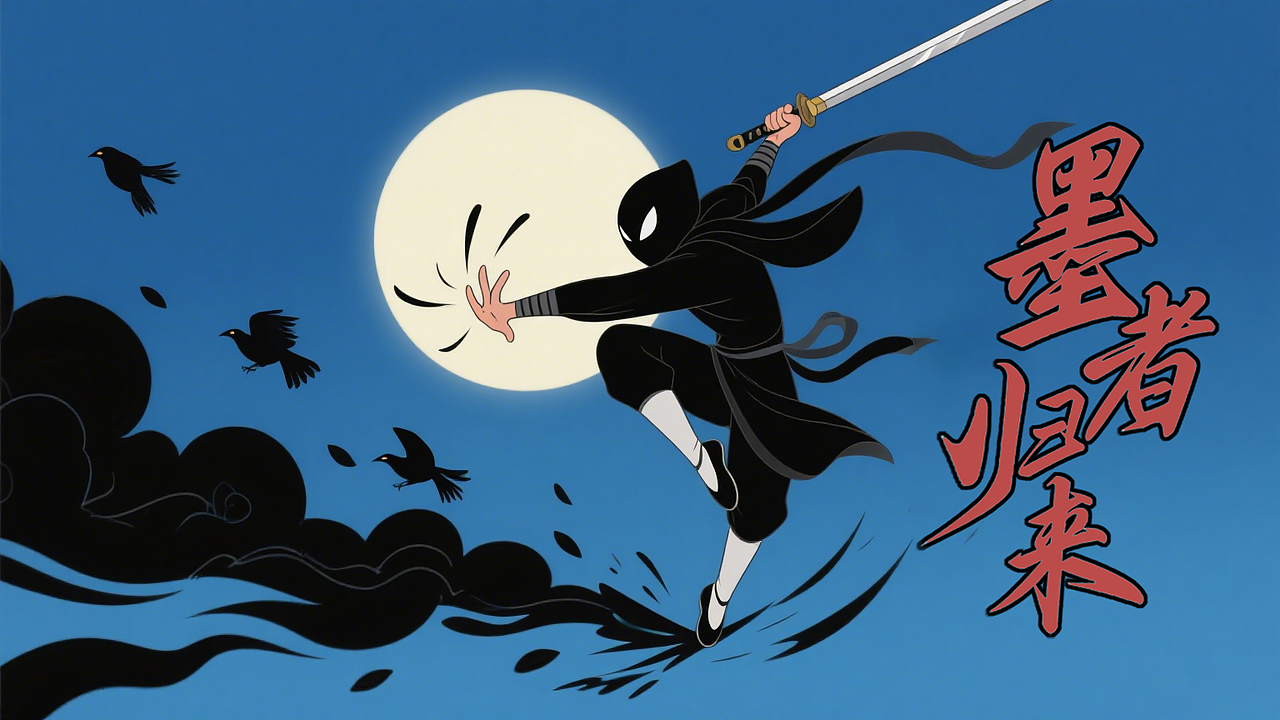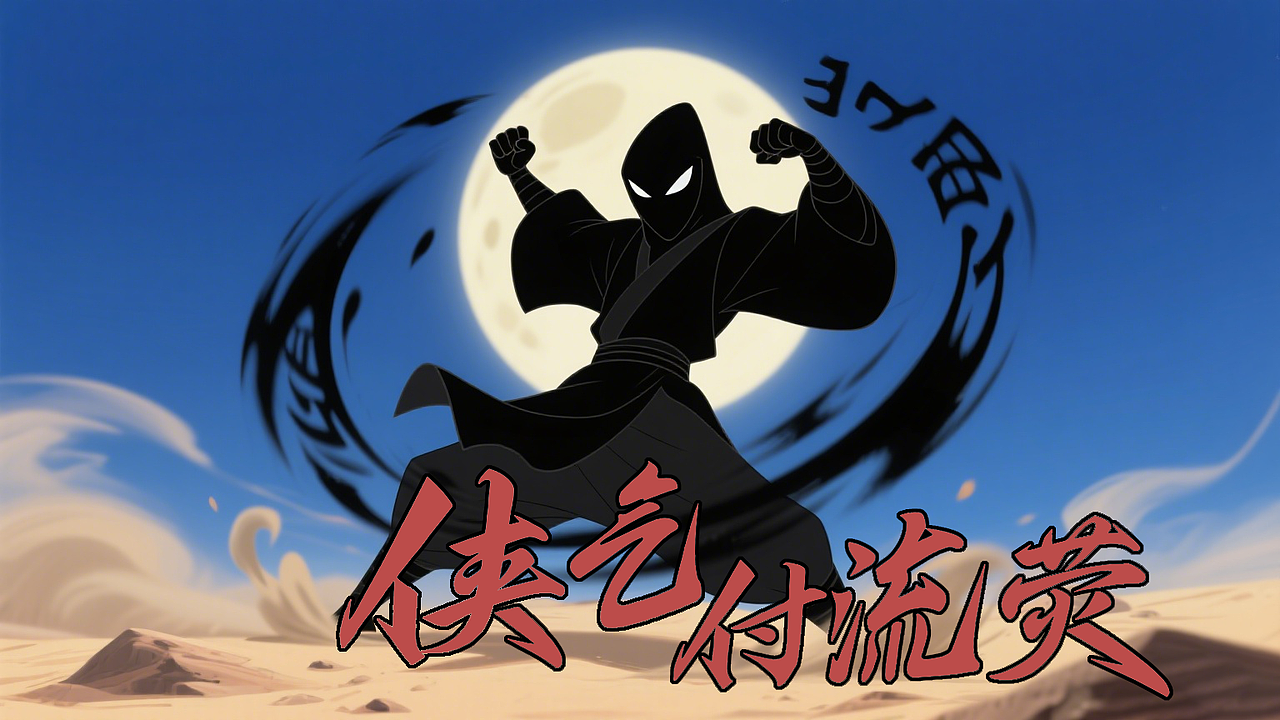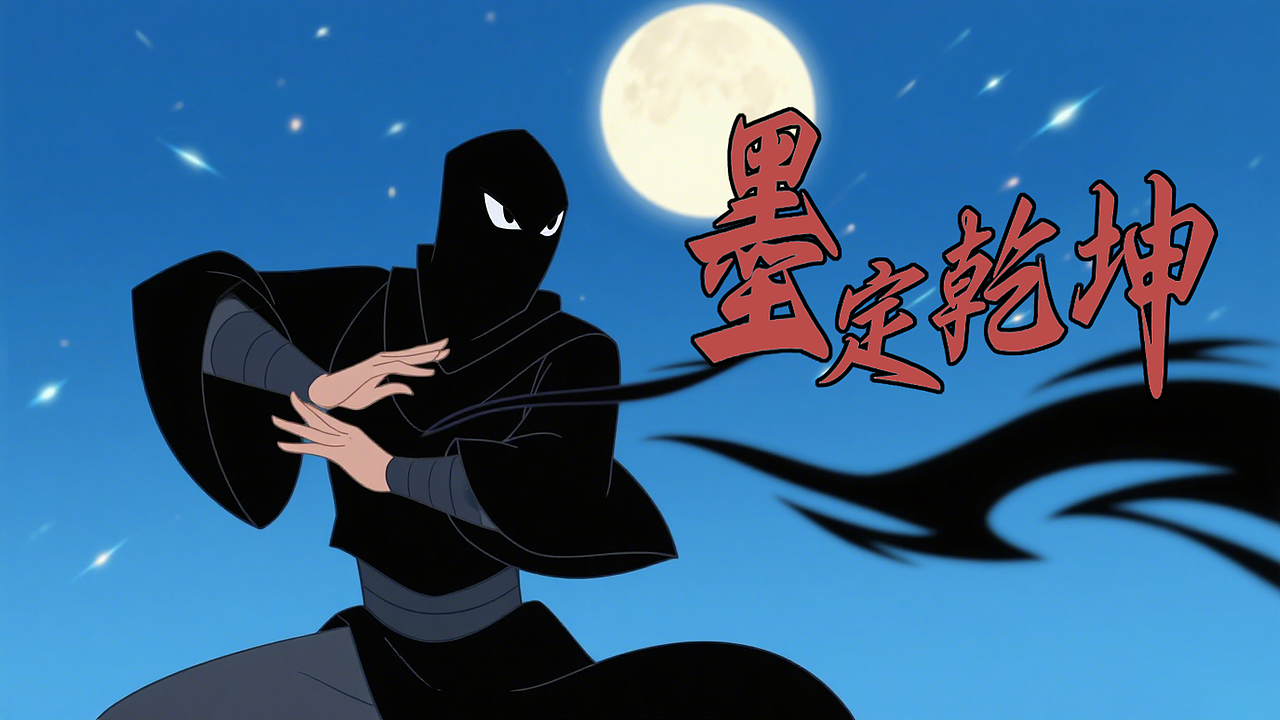
「子漆逍遥行(方正字库)武侠出招表」第三卷
子漆逍遥行的
“可控变形”
,是一场
文字的 “演武场革命”
—— 它让汉字突破静态桎梏,像侠者般 “因势变招”。
子漆逍遥行的核心竞争力在于其可控变形—— 支持斜切、拉伸等操作,使文字可呈现 “腾空剑侠”“策马刀客” 等动态姿态,同时保持汉字识别度。
可控变形的核心是 “守识别,求意境” :即使拉伸 300%、倾斜 45°,文字仍保持辨识度(如 “剑” 字变形后,剑尖的撇画仍如利刃锋锐)。
武侠世界的磅礴,始于一人一剑的墨者传奇,成于一「子漆逍遥行」从不是简单的字体,而是江湖的另一种形态 —— 它让每个字都有了侠者的风骨、武者的气血,在横竖撇捺间铺展万里山河,在笔锋流转中写尽江湖春秋。当它与武侠场景相遇,笔画便化作剑气,文字便成为传奇。
「子漆逍遥行」字体之所以能与武侠场景浑然天成,因其笔锋里藏着江湖的万千气象 。
既有宗师的沉稳如山,亦有侠客的凌厉如风,让每个字都成为江湖故事的生动注脚,在刀光剑影中挥就属于汉字的武侠传奇。